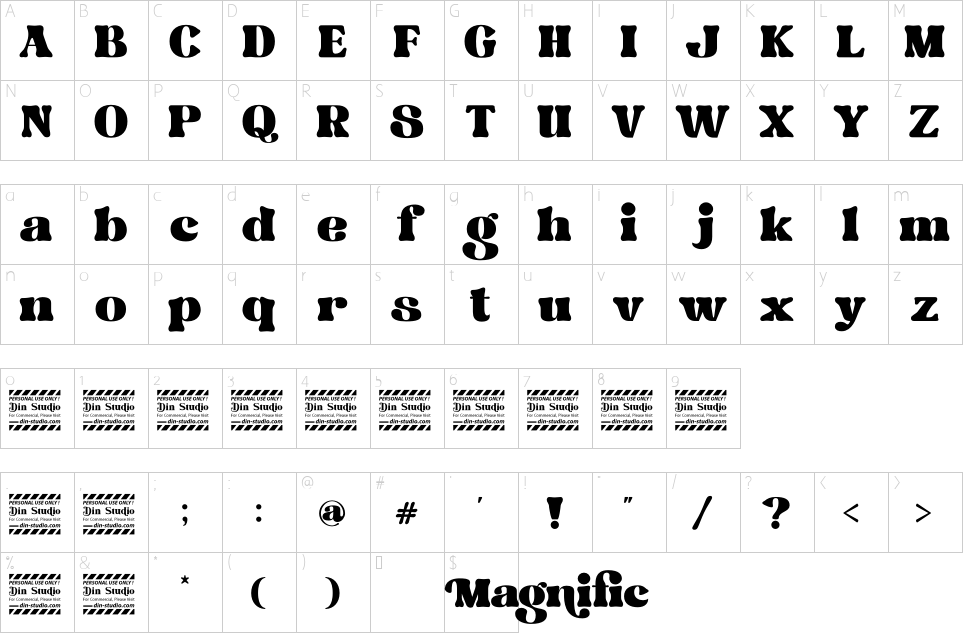
A Magnific Font é uma oferta gratuita para designers e criativos do Brasil, ideal para quem busca uma fonte elegante e versátil. Desenvolvida pelo designer Natha Type, esta fonte vem com 1001 opções e é amplamente utilizada pelos designers gráficos, especialmente para textos legíveis e agradáveis aos olhos. Com sua design simples e elegante, a Magnific Font pode ser usada em diversos tipos de projetos, desde a criação de materiais educativos até a produção de designs gráficos profissionais. É perfeitamente compatível com Windows e Mac, garantindo uma experiência de uso fluida em todos os sistemas operacionais. Se você está buscando uma fonte de qualidade que não custa nada, a Magnific Font é uma ótima escolha.